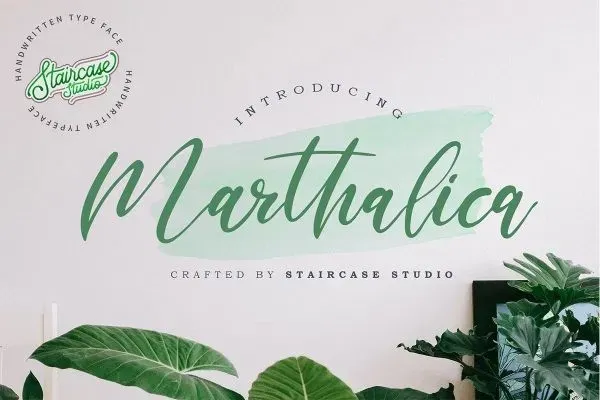
Marthalica Font – Fonte Grátis
Marthalica Font
A Marthalica Font é uma tipografia à mão desenhada que transmite a sensação de relaxamento e fluidez produzida por StairCaseLab. Perfeita para projetos digitais e impressos, essa fonte vai muito bem tanto para logotipos quanto para design de marca, criação de logos, arte digital, aplicações em camisetas ou estampas, folhagens publicitárias, cartazes e anúncios. Esta fonte oferece uma coleção versátil de letras e números que é ideal tanto para projetos digitais quanto para impressão, tornando-a uma escolha valiosa para qualquer necessidade de design. Seja você um designer gráfico ou um amante da arte digital, essa tipografia à mão desenhada está destinada a atender às suas necessidades.